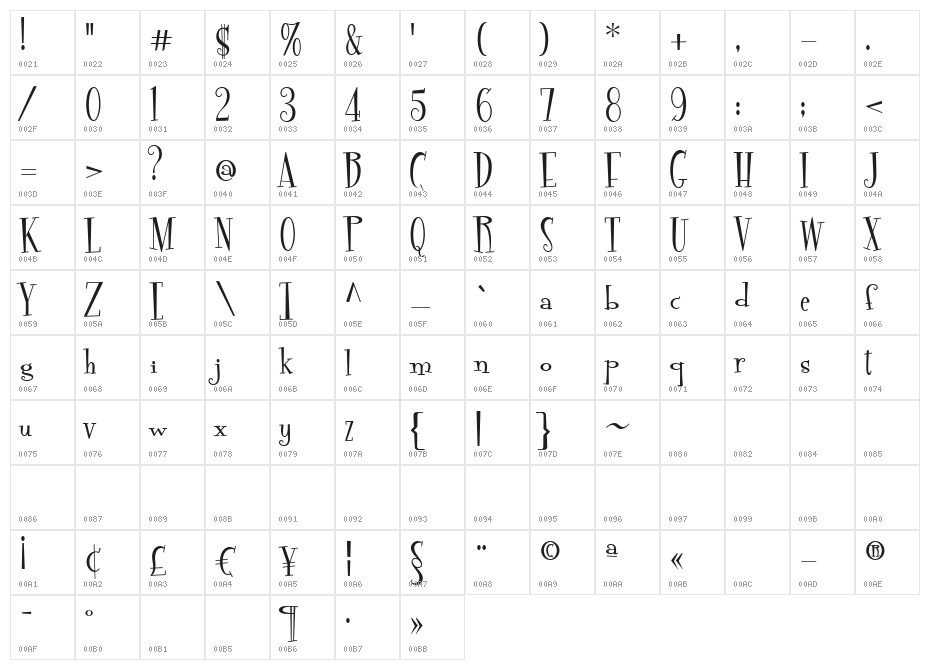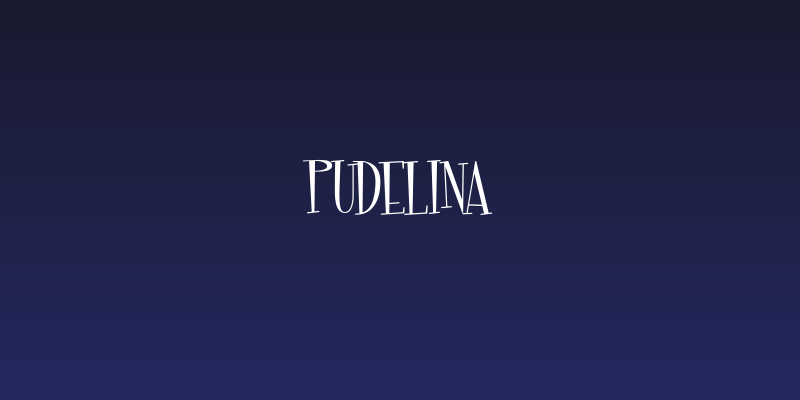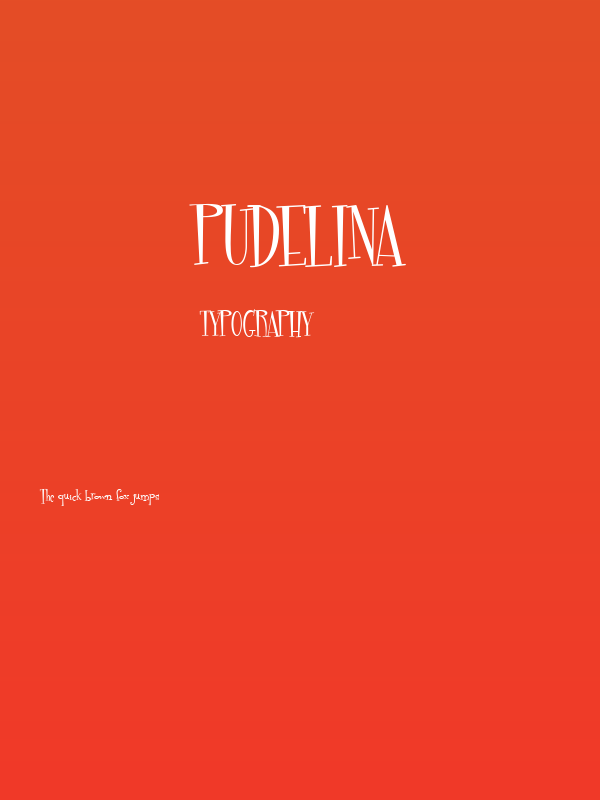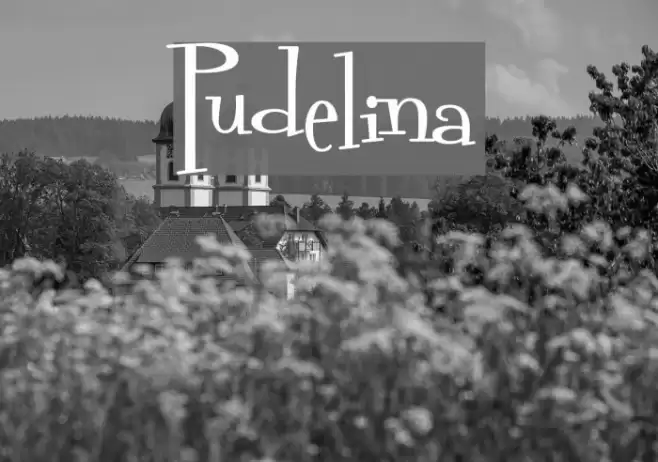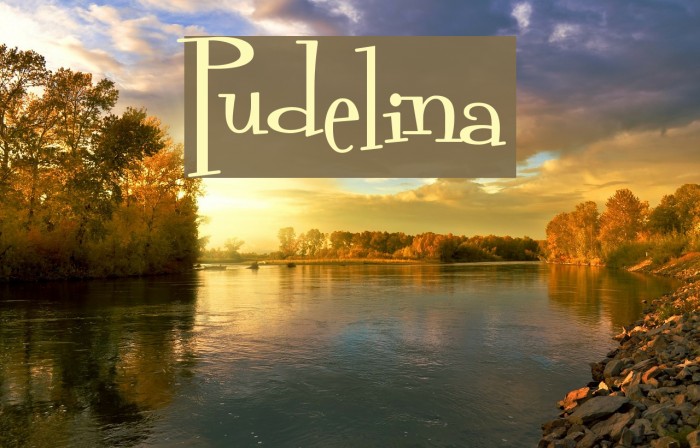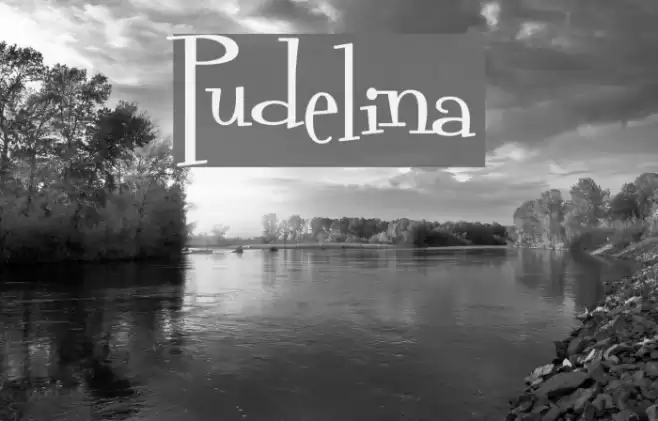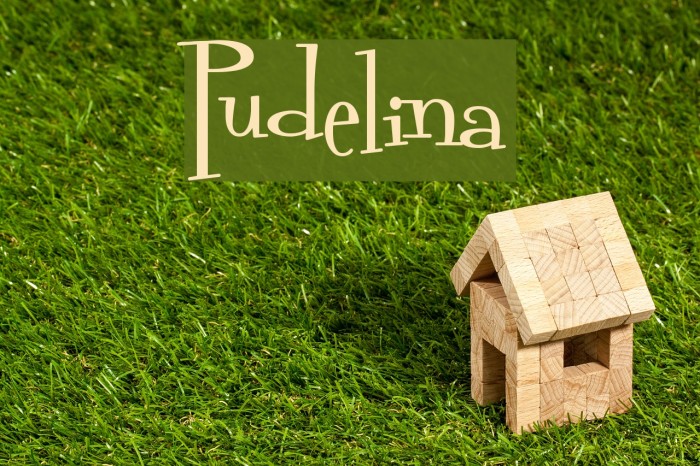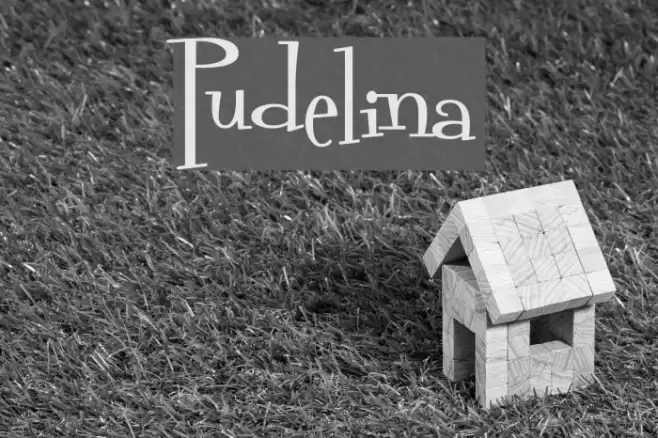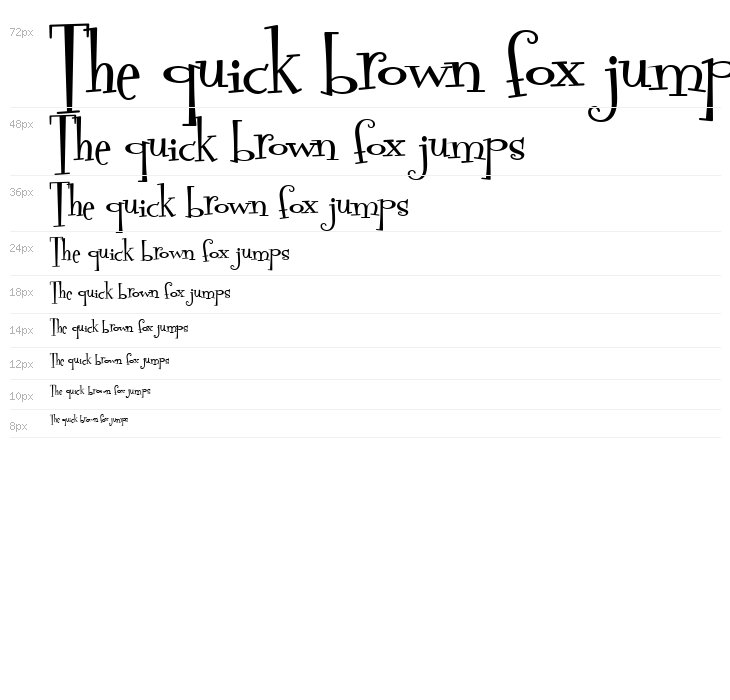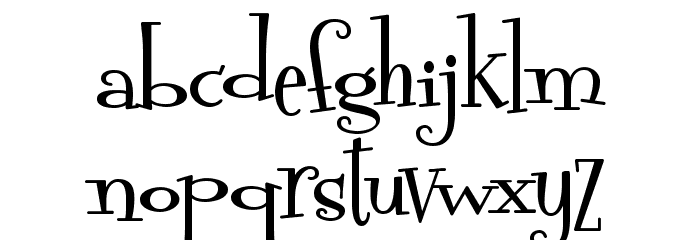
Pudelina Font
| Gesamtstil | Playful, Whimsical |
| Vorgeschlagene Projekte | Ideal for children's books, playful branding, greeting cards, and creative posters. |